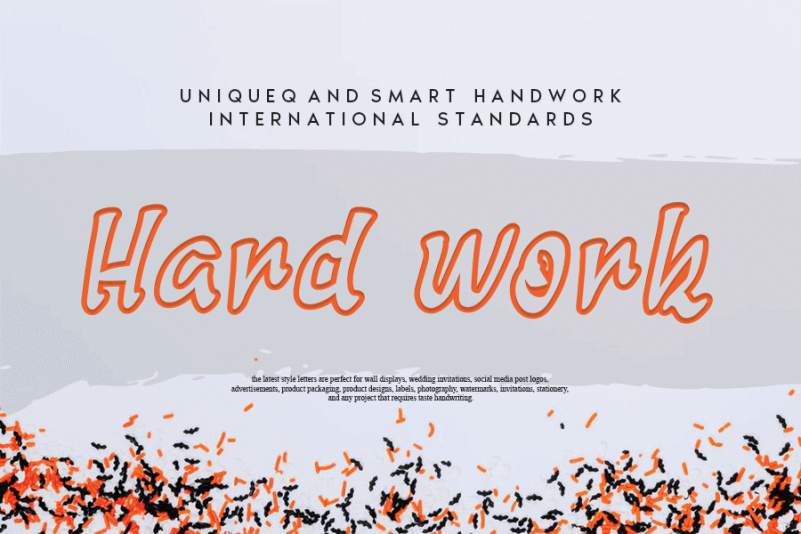
Hard work Display Font
A Hard Work Display Font é uma escolha perfeita para aqueles que buscam um estilo elegante e versátil. Essa fonte desliza com suavidade, promovendo a beleza e sofisticação em qualquer design. Suas características fluidas tornam-a ideal não só para criações de casamento, como cartões de boas-vindas e arte de estação, mas também oferecem uma gama ilimitada de possibilidades no social media. Com essa fonte, você pode criar postagens sociais chamativas que capturam a atenção de seus seguidores. Além disso, sua versatilidade permite seu uso em cartazes, letras de música e até mesmo em publicações institucionais, deixando qualquer projeto mais profissional e imponente. Sem dúvida, a Hard Work Display Font é um recurso gráfico indispensável para designers atentos que desejam estabelecer uma conexão única entre o design visual e os objetivos de comunicação.